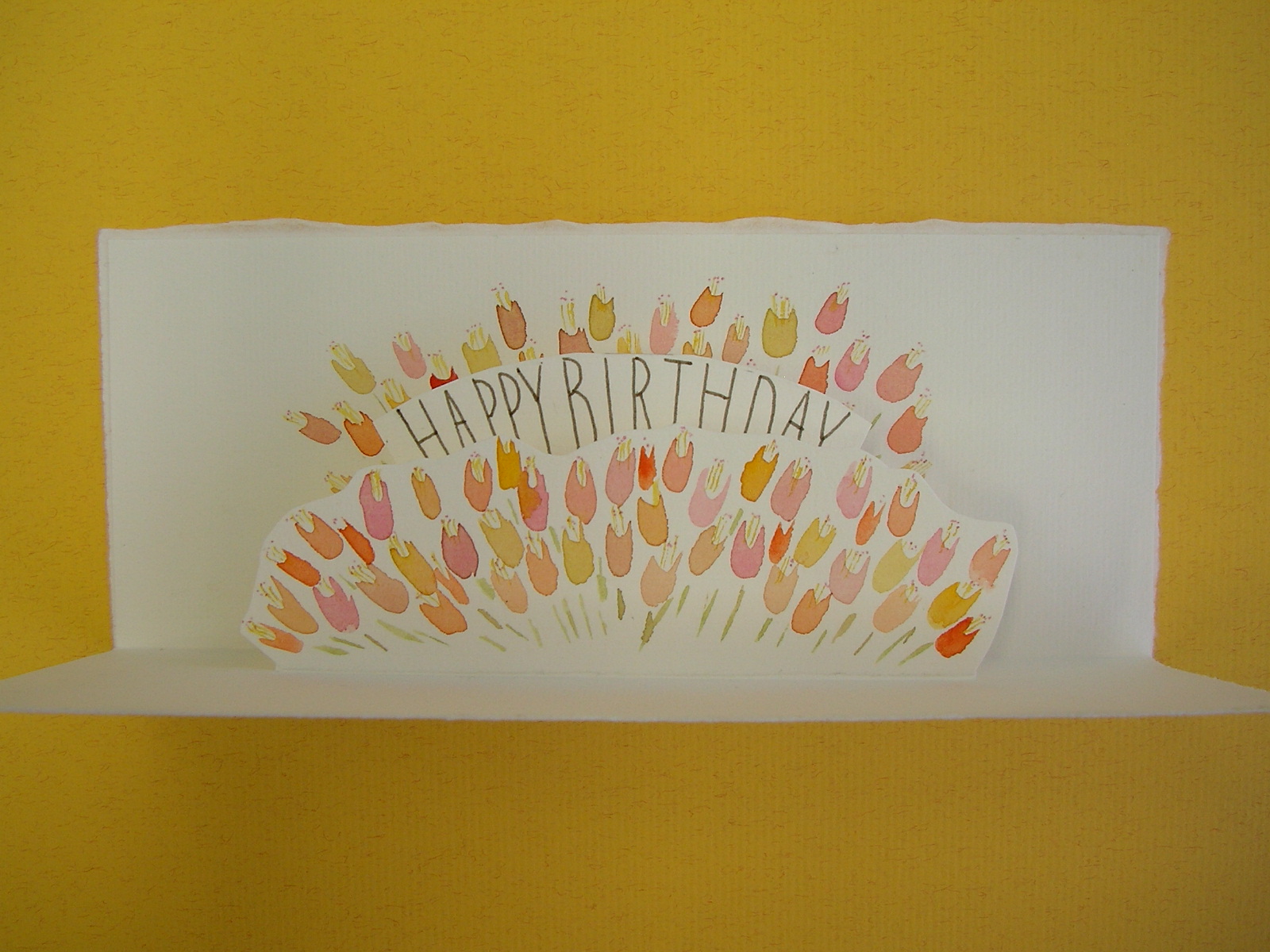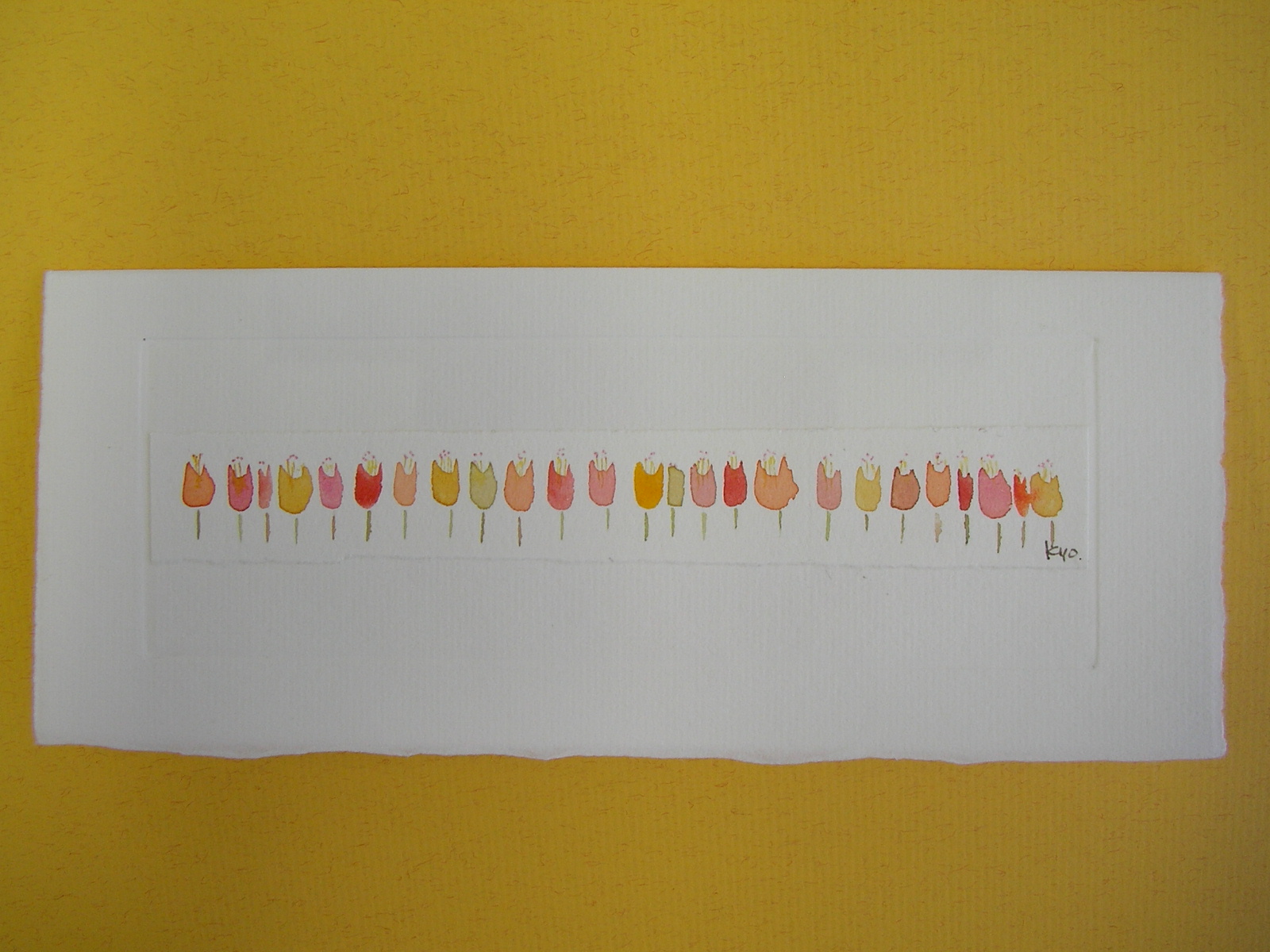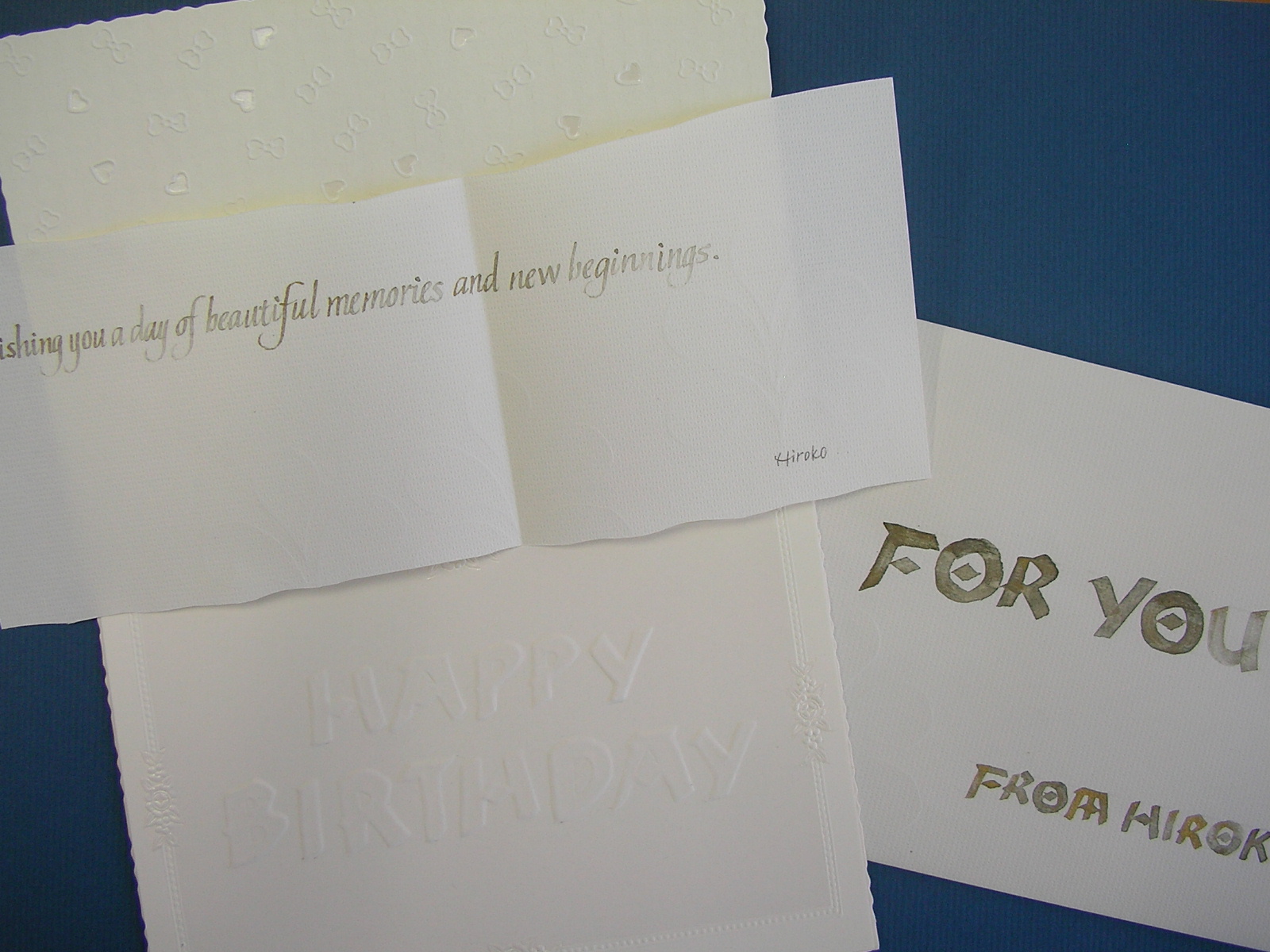
11月の誕生日カード
モジトルカードエクスチェンジの11月のお誕生日カードのご紹介です。
NEさん、AWさん、お誕生日おめでとうございます!蠍座のおふたり、蠍座は、神秘的な魅力の持ち主とか... 早、日は次の射手座に入りましたが、蠍座は、この11月中がとても大切なようです。この一年の始まりの11月のラッキーをしっかりゲットして、また一年素敵に過ごしてくださいね!さて、カードです。
HNさんからNEさんへのカード。
ハンドエンボスのテクニックを十分に使って、シンプルですが、清楚でフォーマルな印象のカードです。
エンボスを写真に撮るのはむずかしく、その良さを伝えきれずとても残念です。いまどきは、機械でエンボス加工された紙類、カードはポピュラーですし、ハンドエンボスのためのツールなんてものも販売されていますが、文字を書き、型を切り抜き、スタイラスで押すという完全オリジナルは、たいしたものでございます。
KYさんからAWさんへのカード。
平筆を使って微妙に変化ある色がきれいな花のパレード。
この表紙にもハンドエンボスが使われています。
そして、開くとお花のたばがぱっと広がるポップアップカードです。
手作りのカードは、形も形式もアイデアしだいで自由にできます。ちょっとたいへんなのは、封筒も合わせて作ることになることでしょうか?!でもこのカードエクスチェンジで、毎回封筒も手作りの方は、封筒作りも慣れましたとおっしゃっていました。